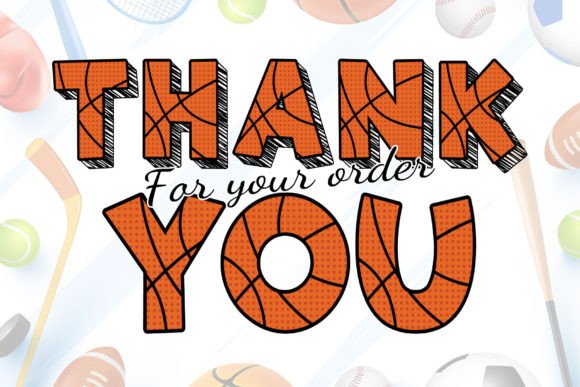
Sport Basketball Font هو خط رياضي احترافي مستوحى من روح كرة السلة، يتميز بتصميم قوي وجريء يعكس ديناميكية اللعبة وحماس المنافسة. مثالي لتصميم الشعارات، أرقام القمصان، البوسترات الرياضية، إعلانات الفعاليات، وتصميمات العلامات التجارية المتعلقة بالرياضة. يتميز الخط بحواف حادة وأسلوب حديث يعزز من وضوح النصوص ويضفي عليها لمسة احترافية مميزة. احصل عليه الآن واجعل تصميماتك أكثر قوة وإبداعًا! ????????